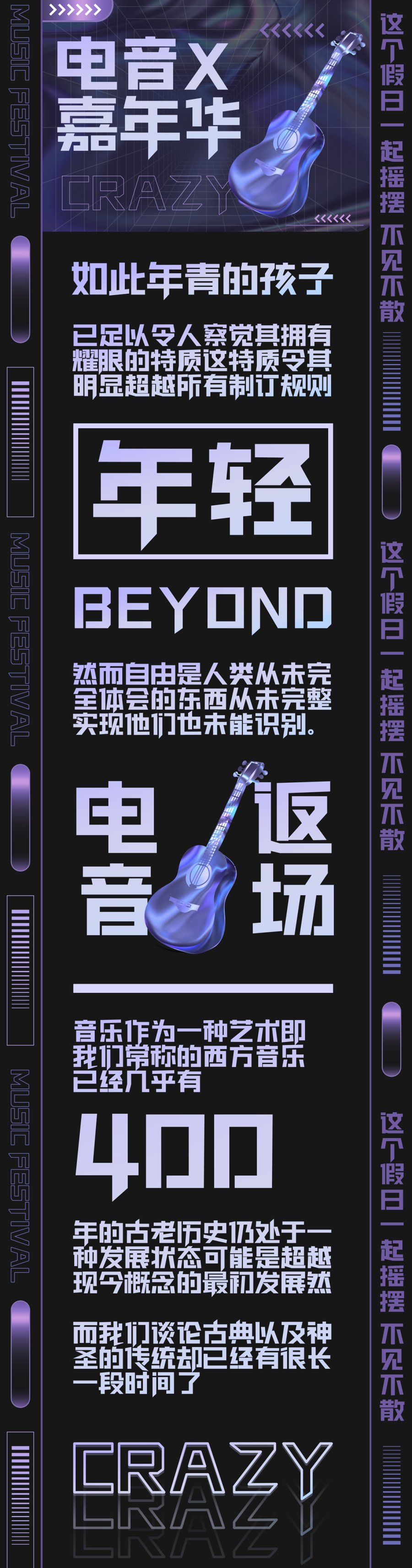
海报中如何运用字体营造科技感?
设计科技感海报时,文字的构成要素越简单,未来感和科技感的感觉就越强烈。表现科技感时,西文的无衬线体要比衬线体更合适,中文的黑体字要比宋体更合适。
印品时尚黑简笔画粗壮有力,布局黑白均匀,整体工整简洁,非常醒目且视觉冲击明显,字体视觉呈现效果更为有科技感。
印品时尚黑简